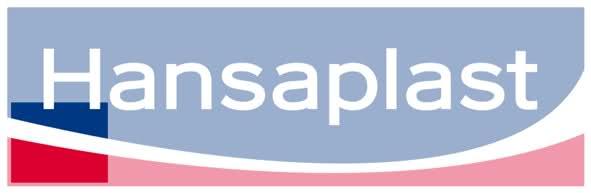
Das lustige Sommerloch-Ratespiel 2009
Ein weiterer Ausschnitt:
Ich nehm ein Roggen-, ein Mehrkorn- und ein Laugenbrötchen, bitte. Als notorischer Frühaufsteher war der Bäcker der Traumberuf in meiner Jugend.
Ja genau, Kamps. :party:
... ich merk’ schon: ohne einen Hinweis bleibt die Typo-Gemeinde heute ratlos. :oops:
Das gesuchte Logo ist eine aus nur wenigen Silben bestehende Wortmarke.
Zum Einsatz kommt eine statische Grotesk ...
Ist das ein ??
nein. ok, es scheint wirklich zu schwer zu sein, oder? :neenee:
technik, kein deutsches unternehmen ...
neuer ausschnitt
wenn ich jetzt noch sage das es teuer und etwas prollig ist habt ihr es gleich ...
Kenwood – Ferrari – Rolex. Alles Fehlanzeige. Ich gestehe: ich habe keine Ahnung.
Der neue Ausschnitt sagt mir noch weniger als der alte … :? :cry:
letzter tipp für heute sonst kommt morgen ein neuer ausschnitt:
dänischer hersteller. auf der webseite wird das logo nicht in der hier gezeigten version verwendet, der erste ausschnitt funktioniert trotzdem.
Hallo. Ich glaube, es ist Bang & Olufsen.